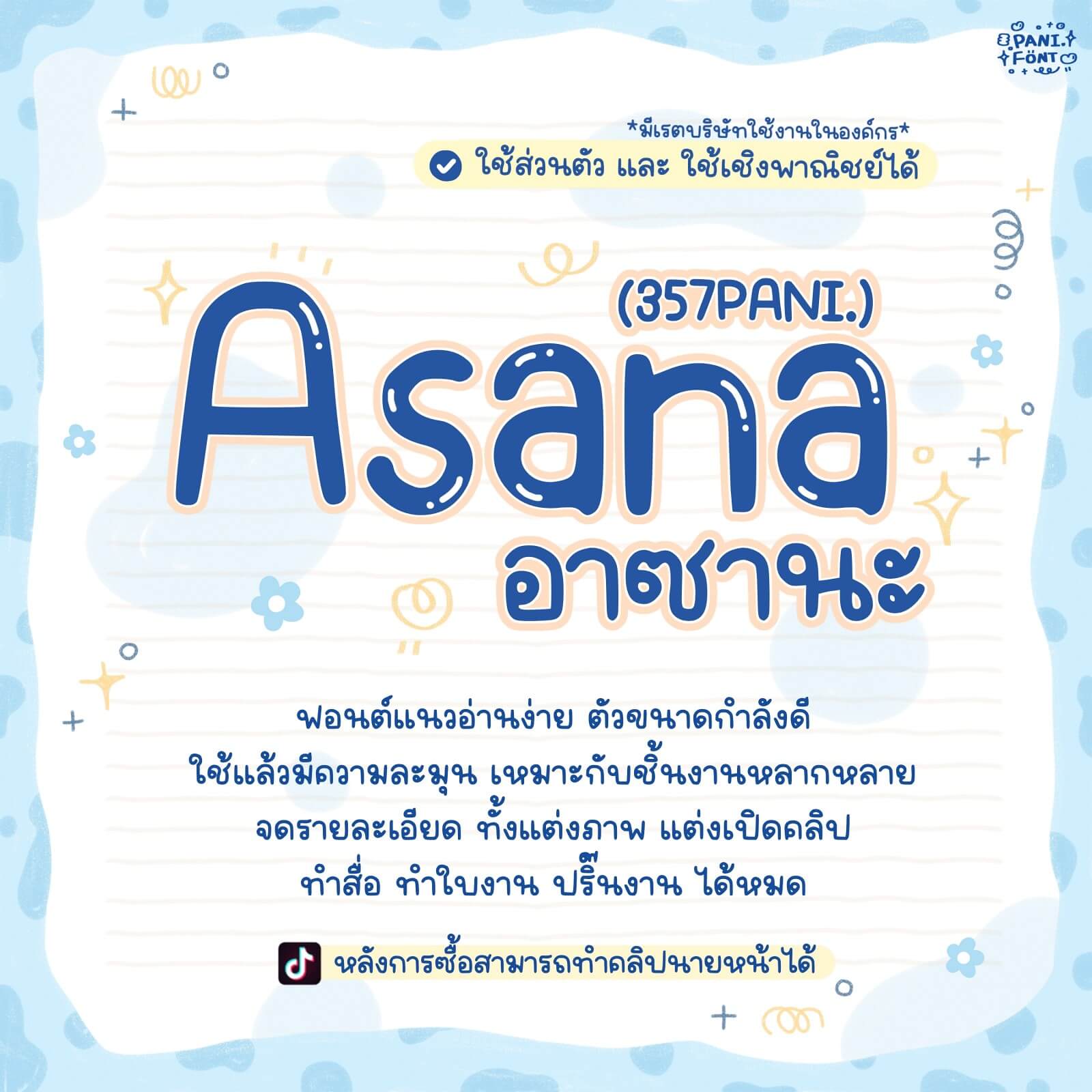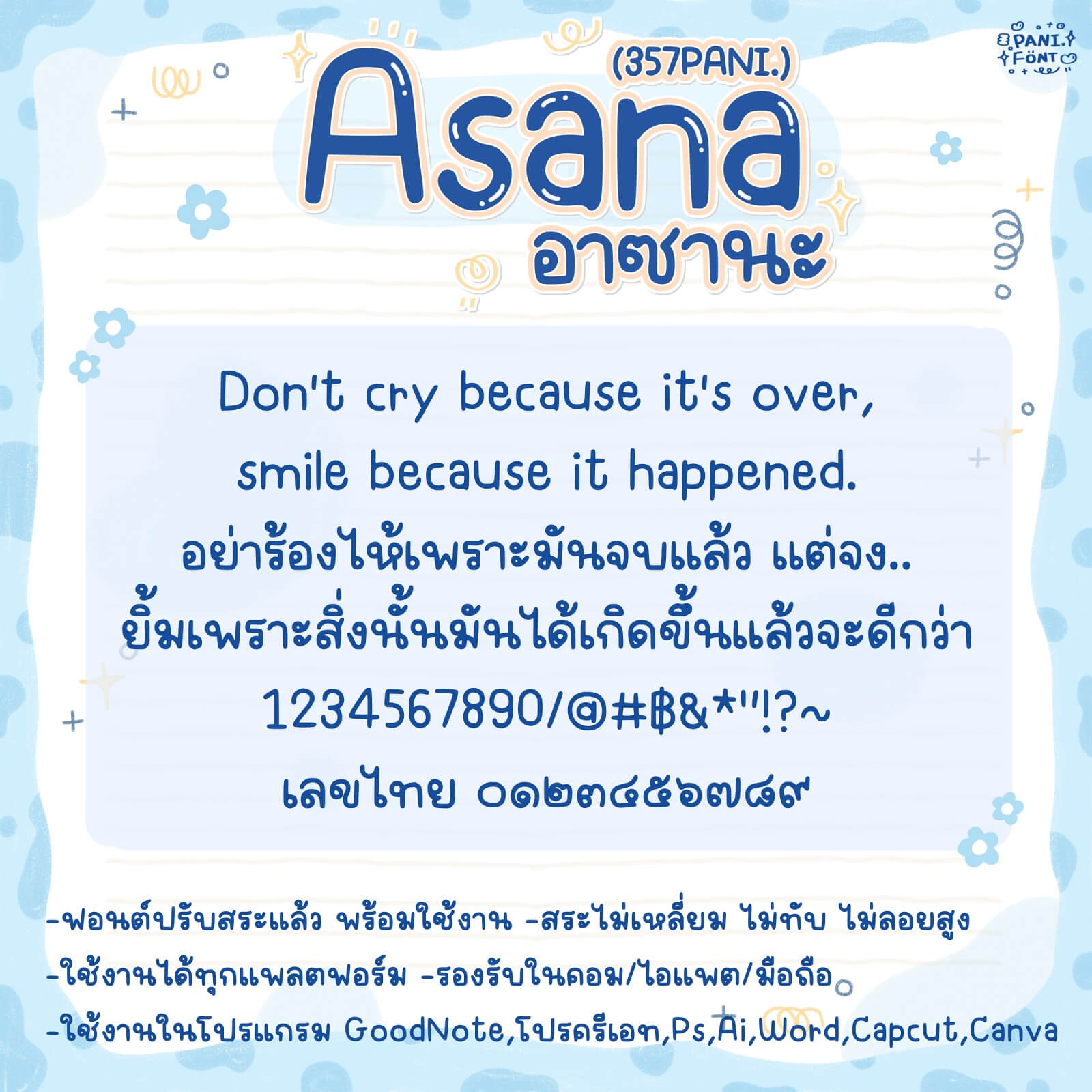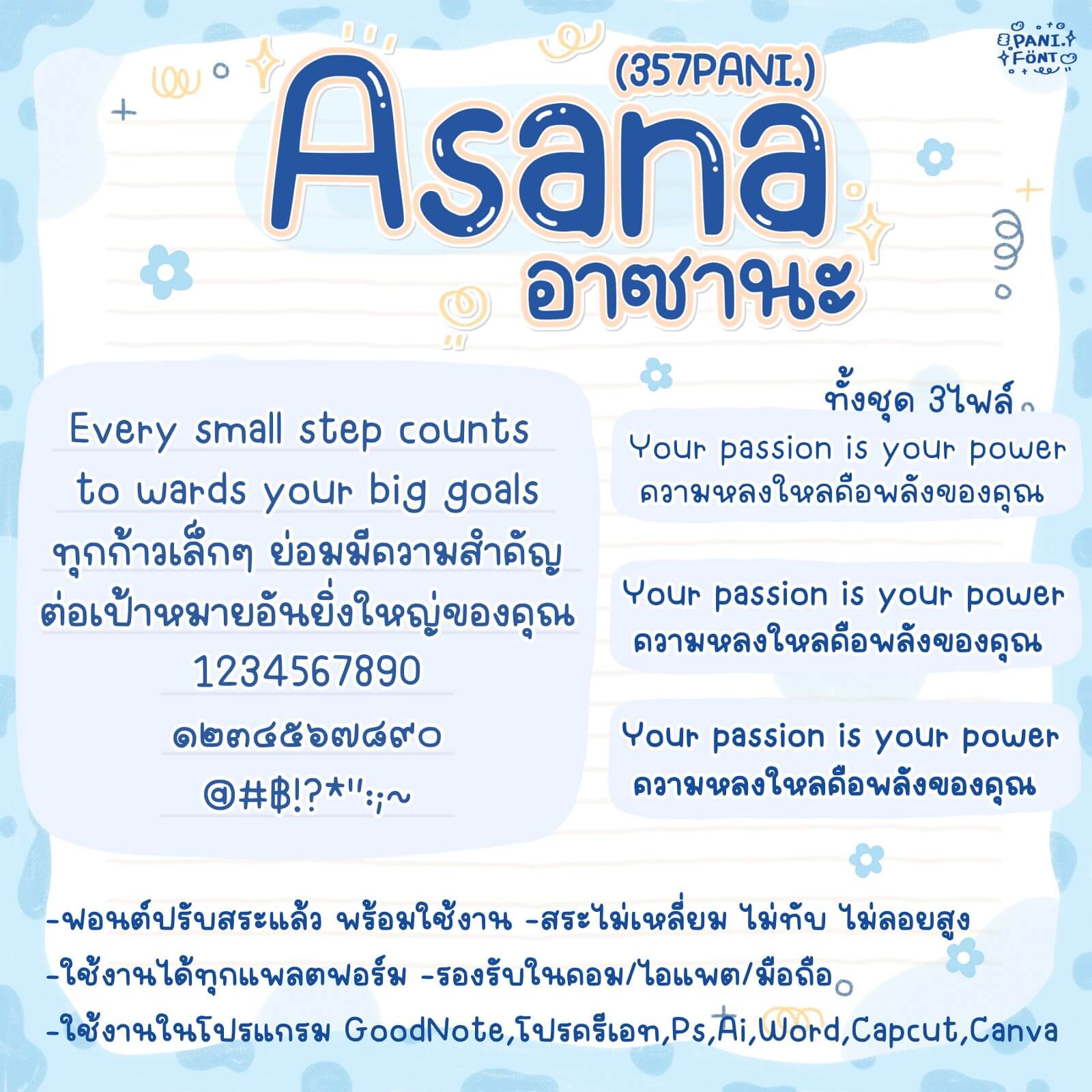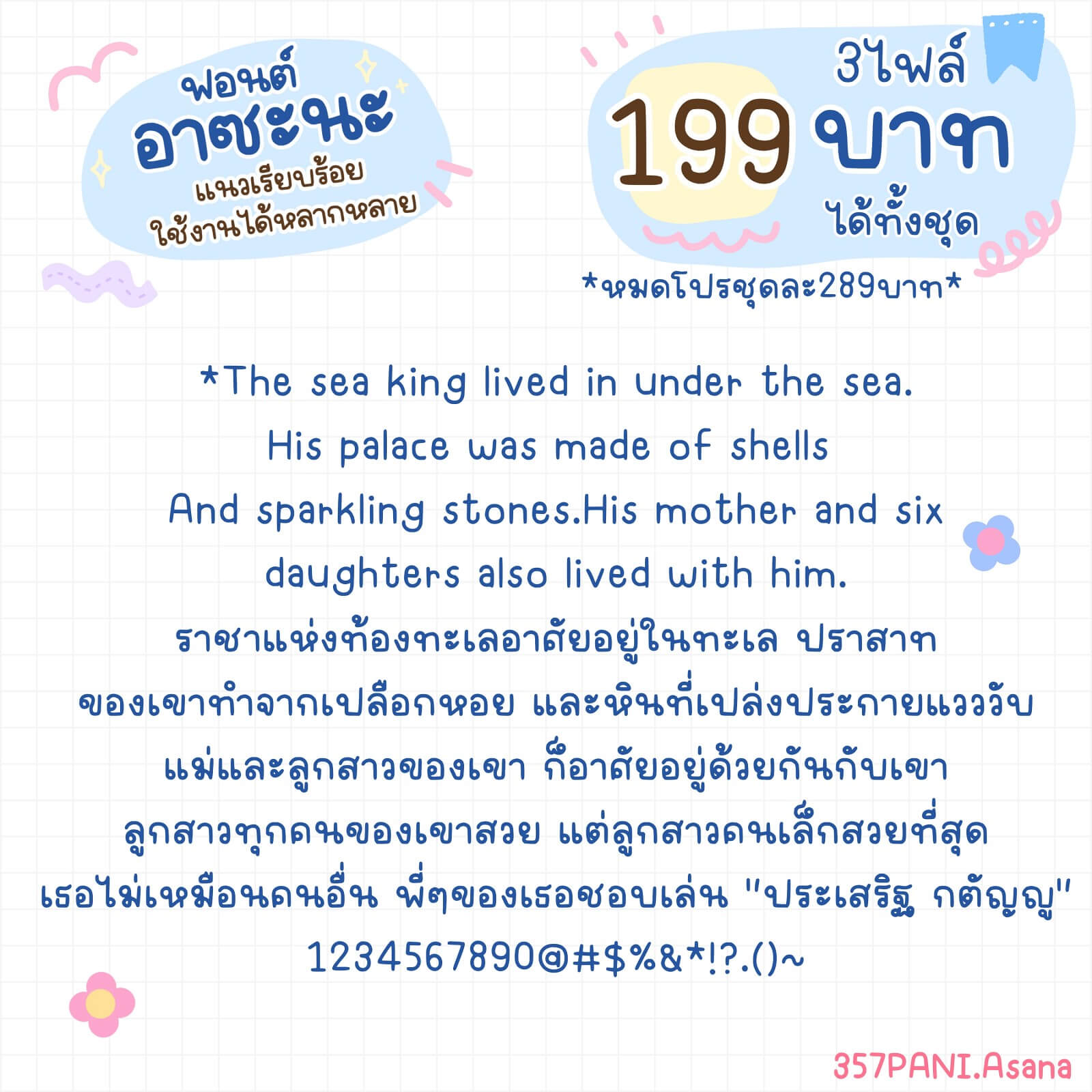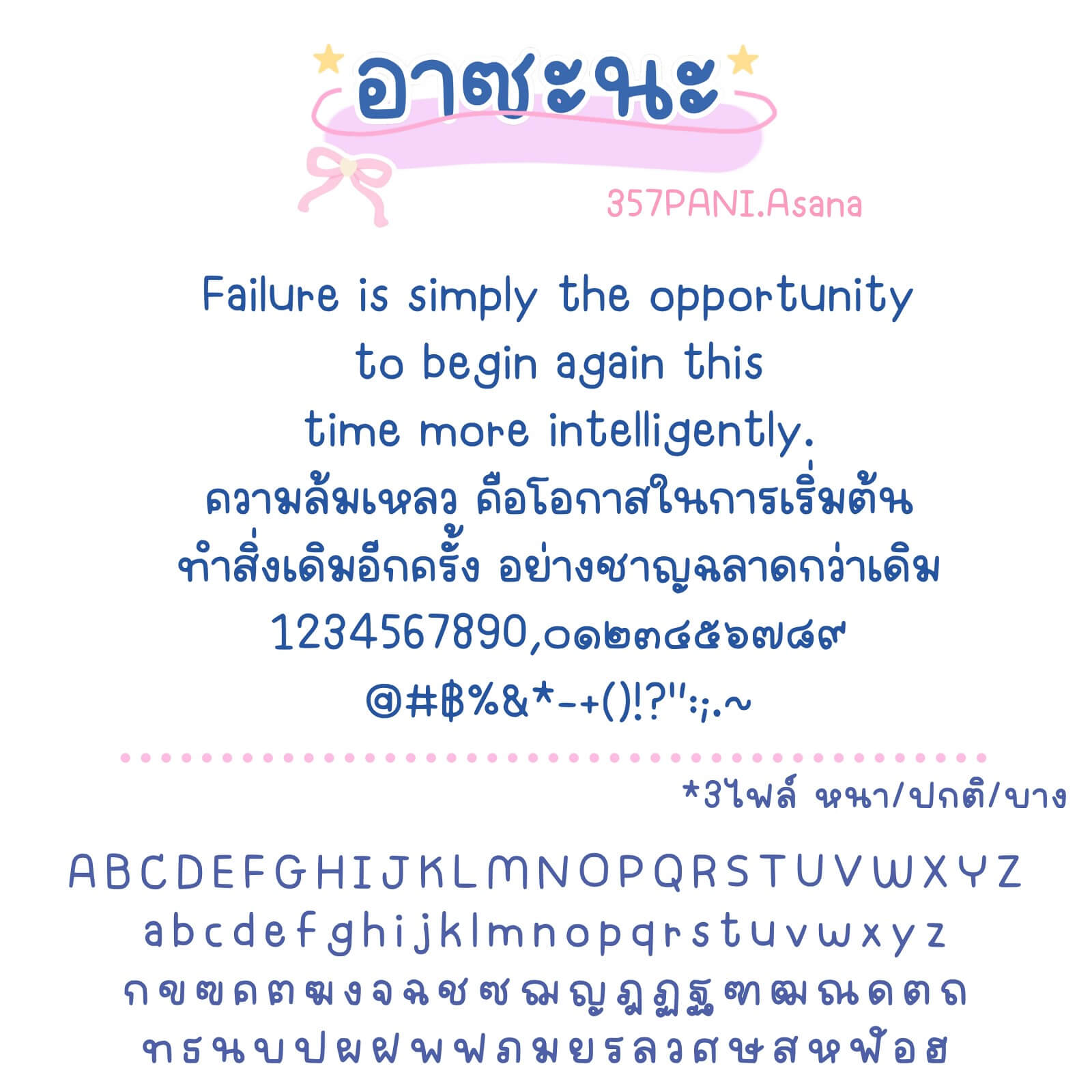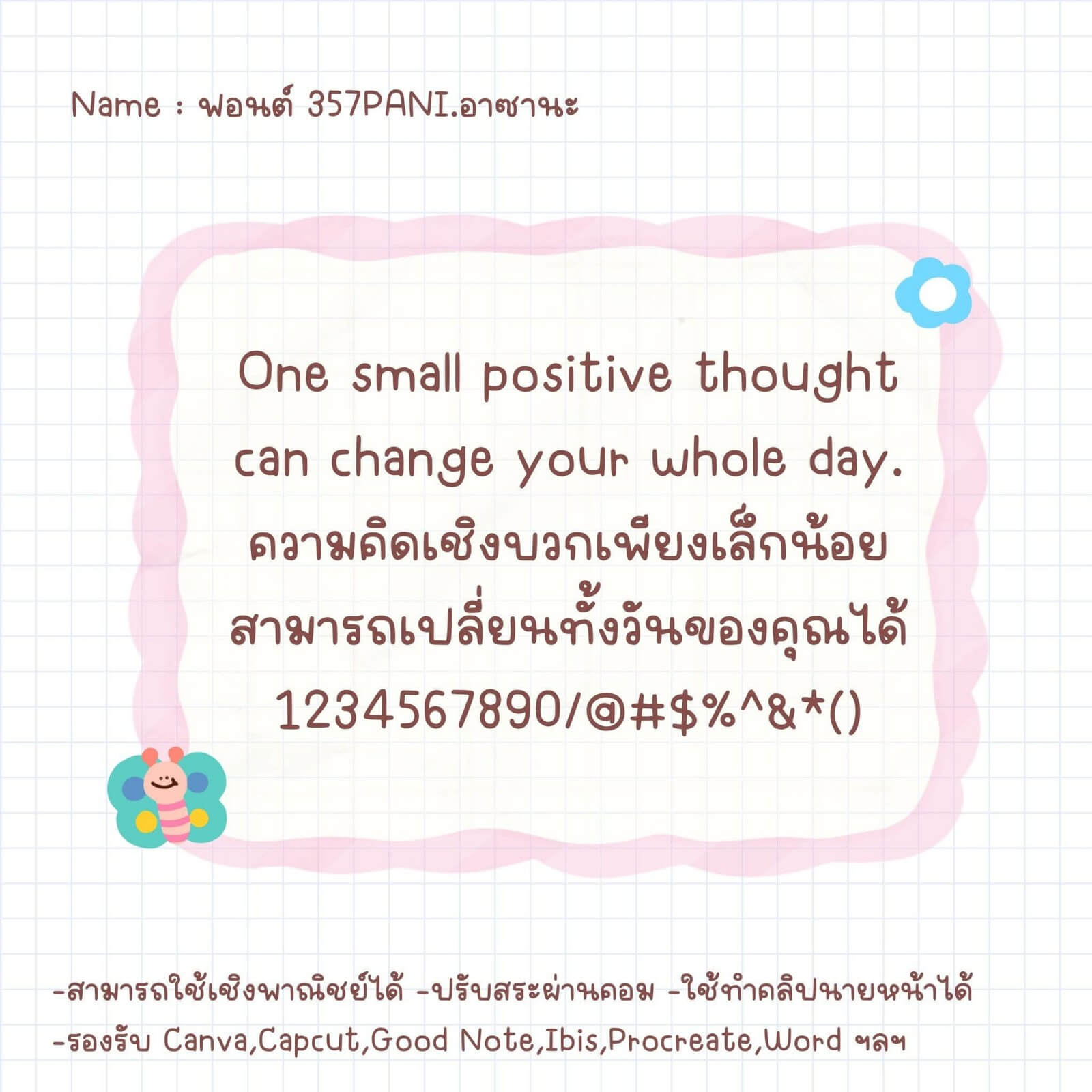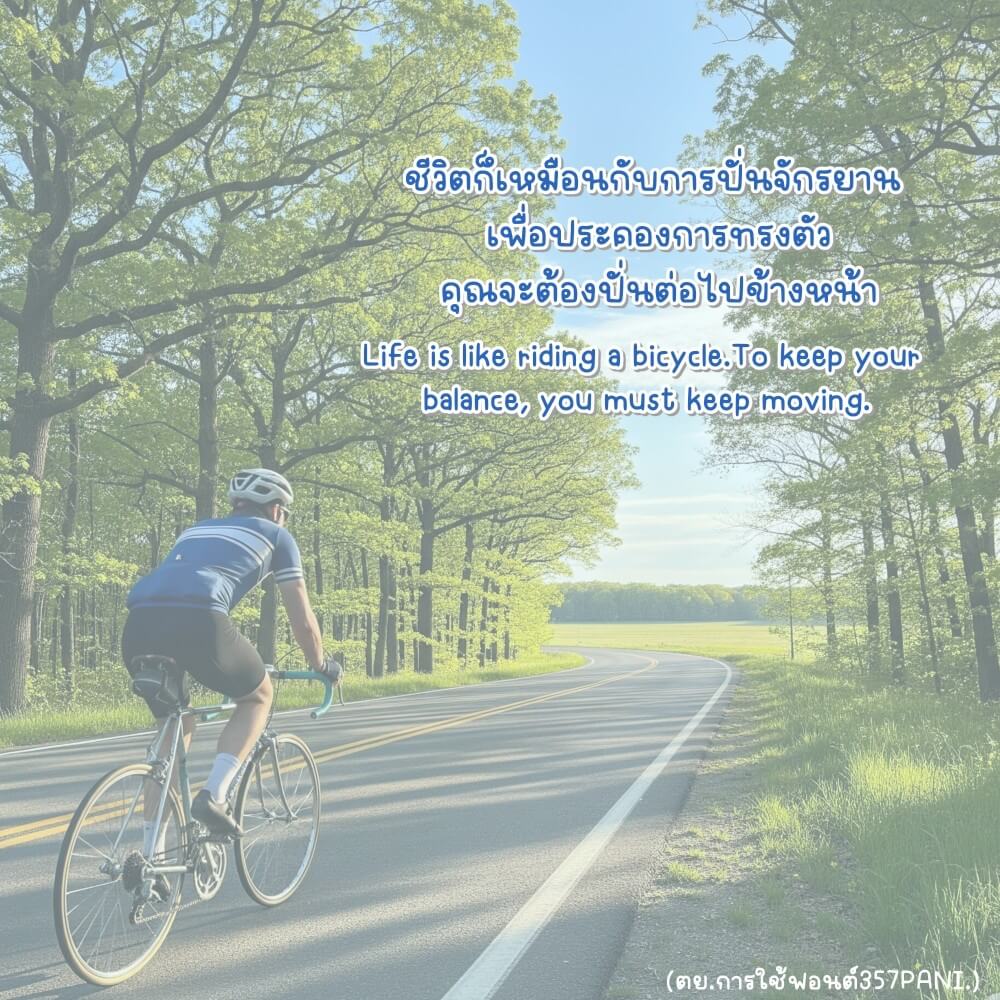
ฟอนต์ 357PANI.อาซานะ – ฟอนต์แนวอ่านง่าย ตัวขนาดกำลังดี ใช้แล้วมีความละมุน เหมาะกับชิ้นงานหลากหลาย จดรายละเอียด ทั้งแต่งภาพ แต่งเปิดคลิป ทำสื่อ ทำใบงาน พรินต์งาน ดูเด่น ไม่เยอะเกินไป
357PANI.อาซานะ